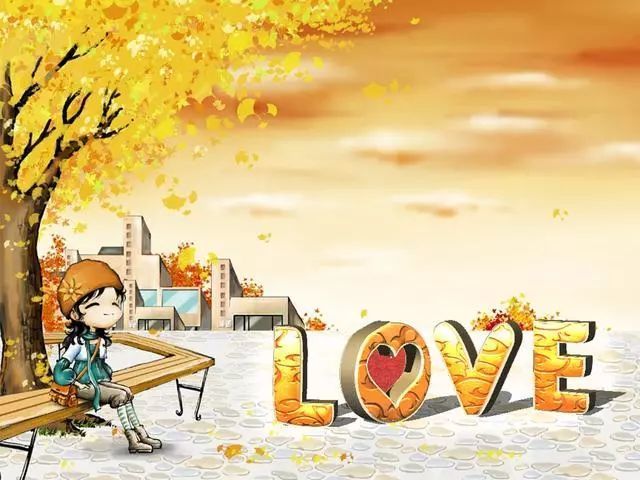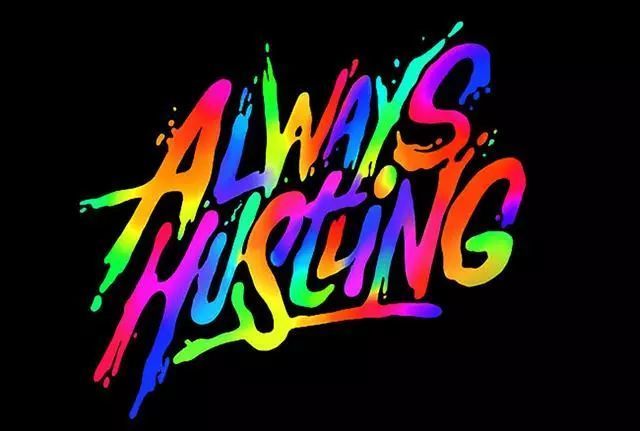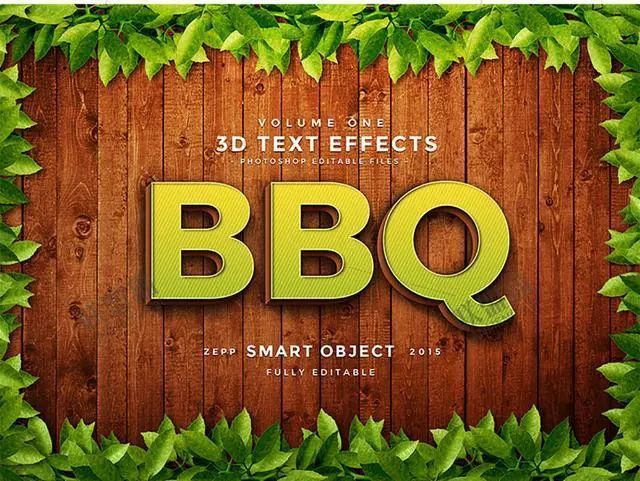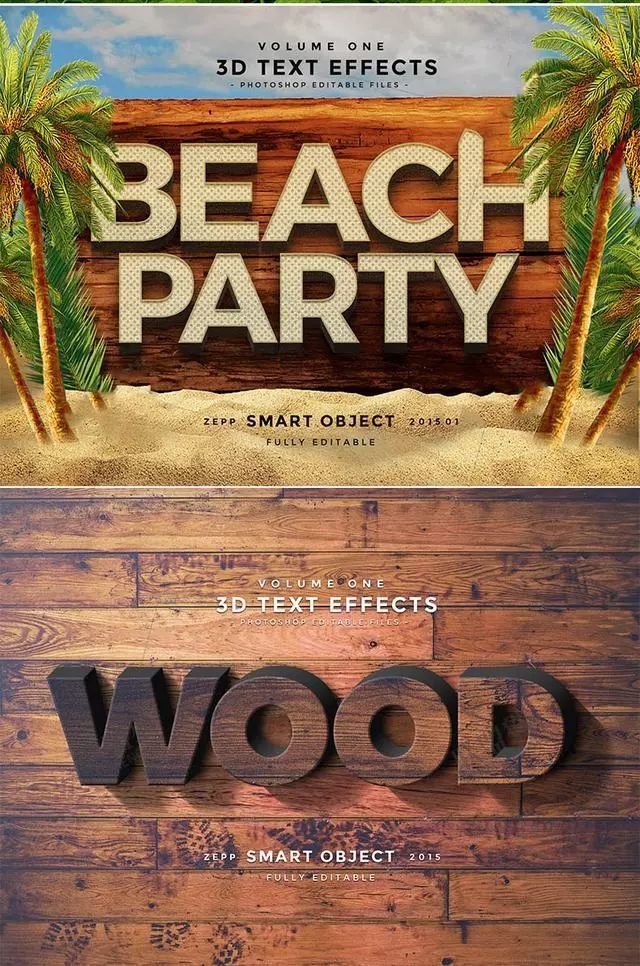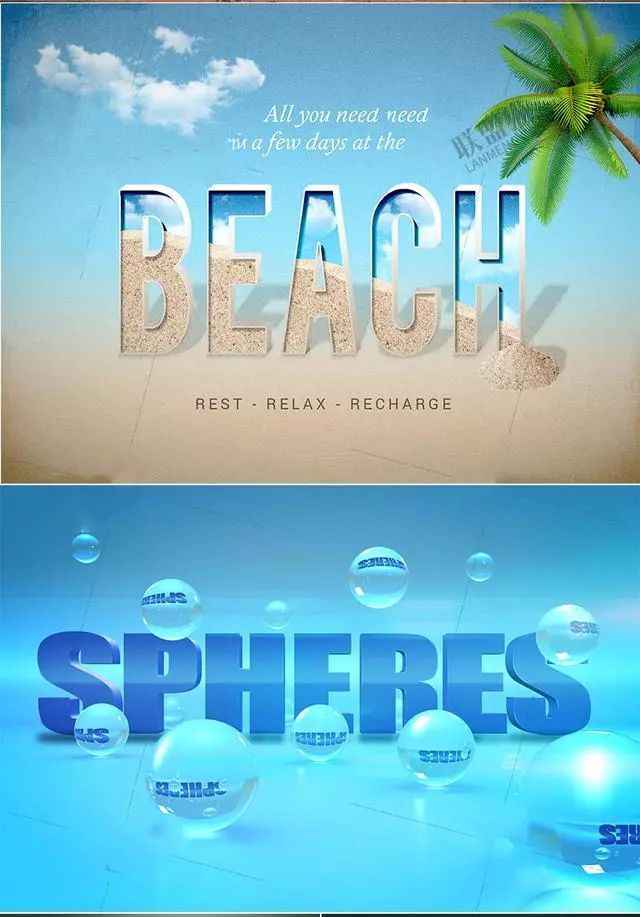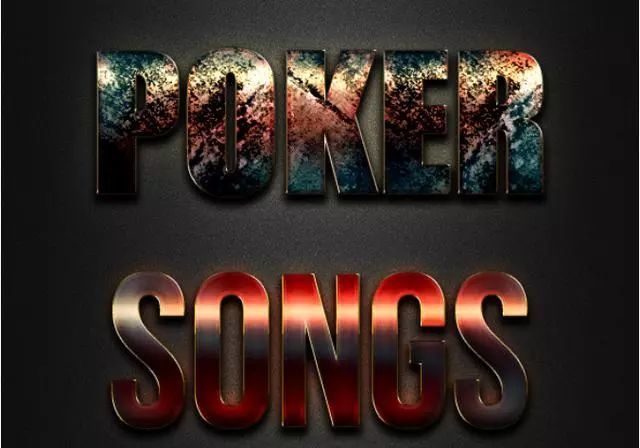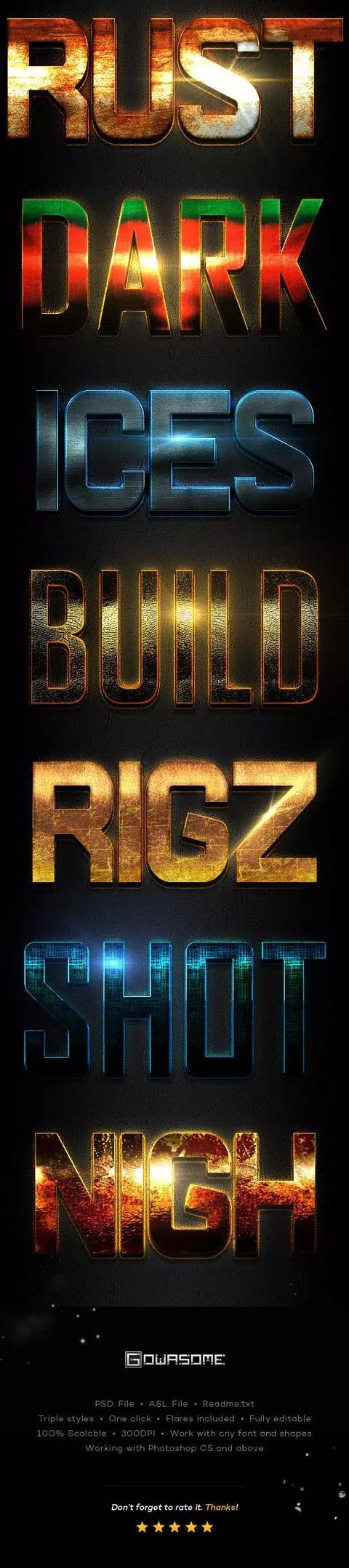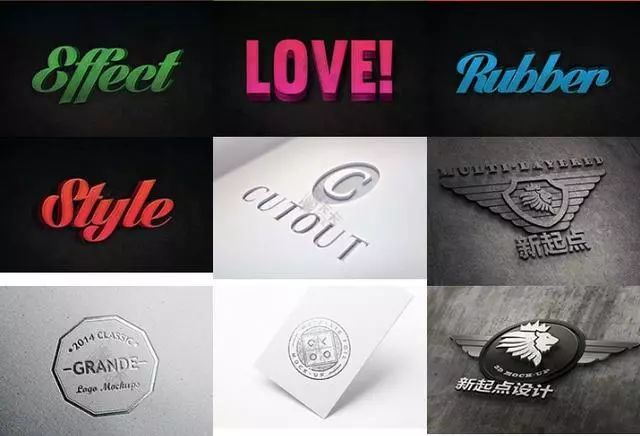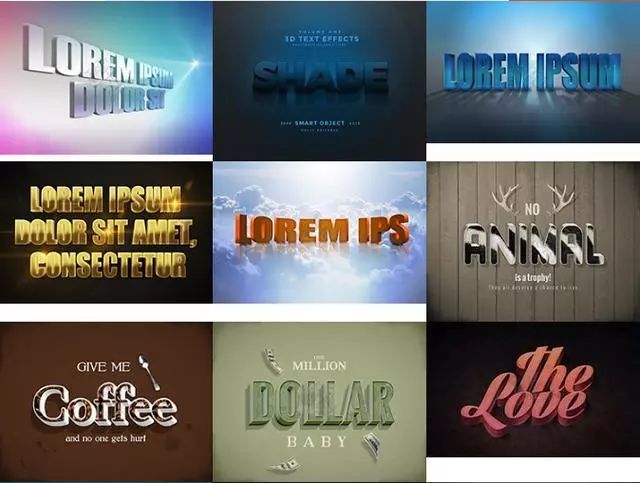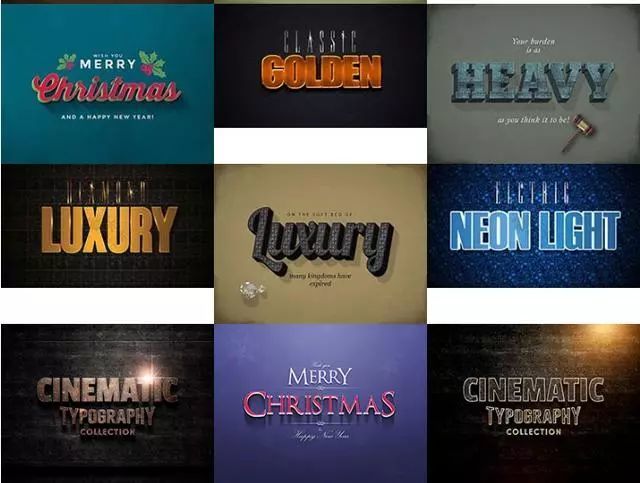
字体效果在页面中也起着很重要的作用,用好了字体效果可以很好的烘托出页面的气氛,我们见到过火焰字体、金属字体、黄金字体的效果。
大家有没有发现,当你被某个海报或广告牌的设计作品吸引时,第一眼看到的不是他的背景图和插画设计,也不是它的排版多么好。而是它的字体效果,炫酷的字体效果能立马就抓住你的注意力。
包括:复仇者联盟字体效果、哥特黑暗风字体效果、黄金字体、金属特效、圣诞节字体效果、自然主题字体效果、火焰燃烧字体效果、黑板粉笔字体效果、彩色文理字体效果、复古字体效果、D立体字体效果等。